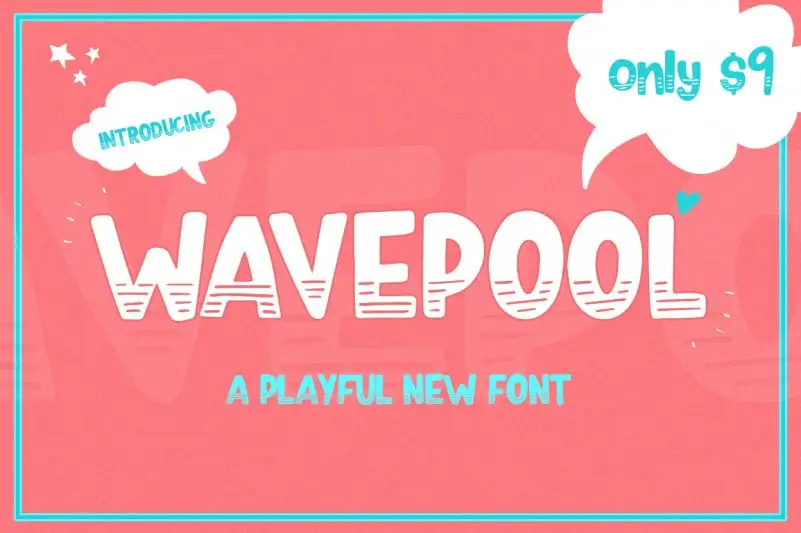
Wavepool Font – Download Grátis
Wavepool é uma nova fonte sem serif que traz com ela um toque leve e divertido. Disponível para apenas R$ 9,00 no formato de fonte, Wavepool está completamente compatível com todas as versões de programas populares, incluindo Microsoft Word, Photoshop, Silhouette Studio, Cricut Maker entre outros. Seja você designer ou amante do design, Wavepool é uma escolha perfeita para adicionar um toque único à sua próxima criação digital. Com a facilidade e versatilidade de uso deste fonte, você pode experimentar essa criatividade em diversos ambientes e aplicações da arte visual. Sua disponibilidade no formato de fonte, também significa que é fácil adaptar o estilo para diferentes necessidades ou estilos, tornando-a uma opção de verdadeira economia de tempo no processo criativo. Não perca esta oportunidade para trazer um ar descontraído e moderno a seus projetos com Wavepool Font.